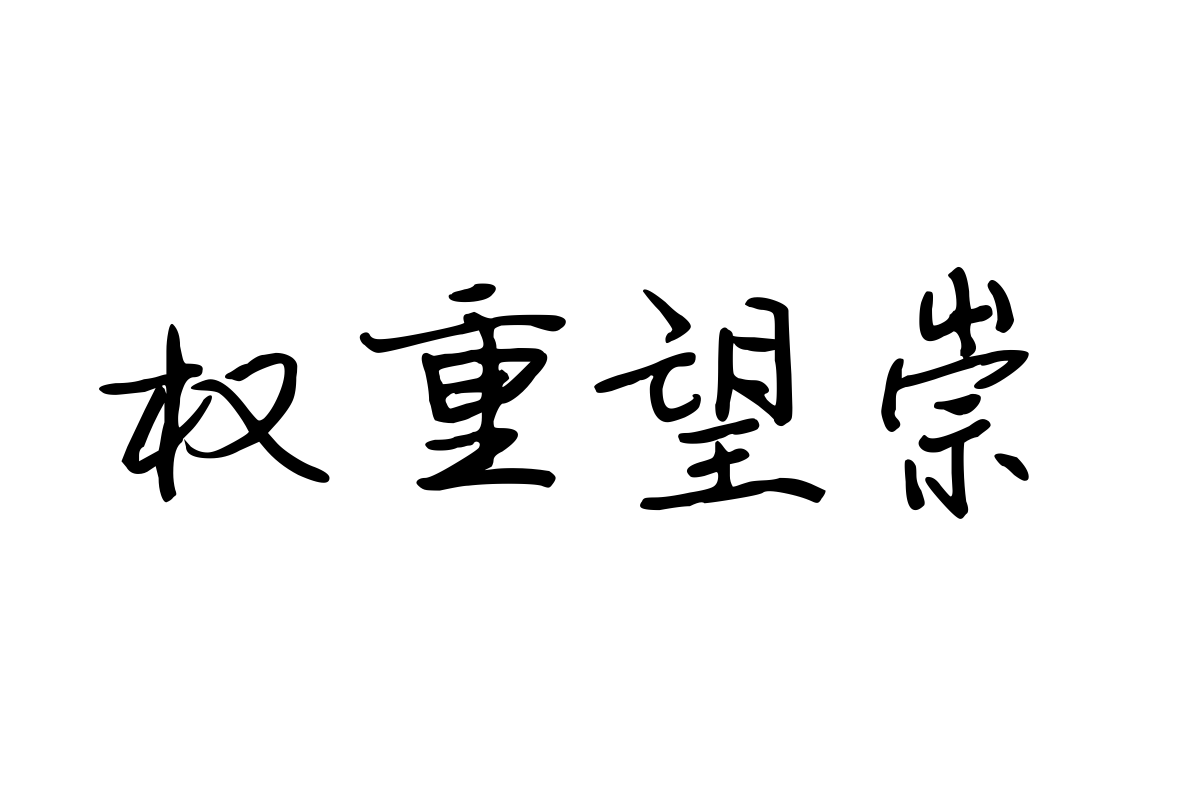
三极陌州行楷字体是一种具有独特风格的汉字书写风格,它源自中国古代的书法艺术。这种字体的特点是笔画流畅、结构紧密,线条粗细变化丰富,既有行书的舒展,又有楷书的规整。
三极陌州行楷字体的主要特点如下:
1. 笔画流畅:这种字体的笔画线条流畅自然,没有过多的停顿和转折,给人一种流畅的感觉。
2. 结构紧密:虽然笔画流畅,但每个字的结构都非常紧凑,字形大小、间距都经过精心设计,使得整个字体看起来非常整齐。
3. 线条粗细变化丰富:这种字体的线条粗细变化丰富,既有细如发丝的线条,也有粗如椽木的线条,使得整个字体看起来非常有层次感。
4. 规整与自由相结合:虽然线条粗细变化丰富,但每个字的结构都非常规整,没有过多的随意性,这使得整个字体看起来非常规整。
5. 适应性强:这种字体适用于各种场合,无论是正式的公文、报告,还是日常的书信、日记,都能很好地适应。
总的来说,三极陌州行楷字体是一种具有独特风格的汉字书写风格,它既保留了行书的舒展,又兼顾了楷书的规整,线条流畅而富有变化,结构紧凑而富有层次感,是汉字书法艺术中的一种重要流派。